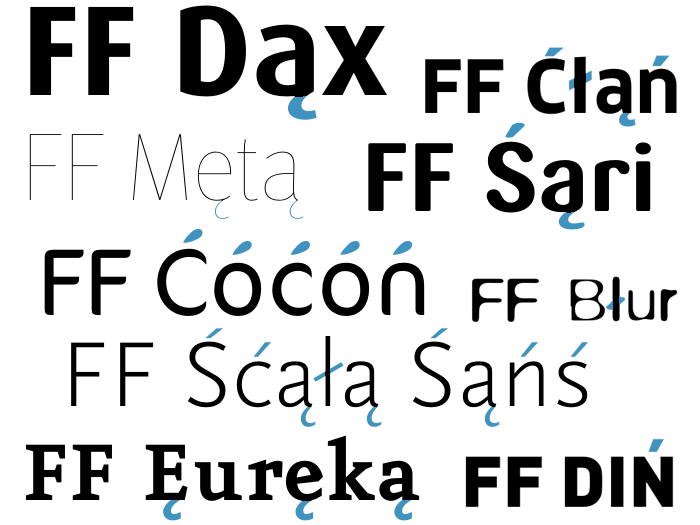
FontShop International - firma
Firmę FontShop International założyli w 1990 roku Erik Spiekermann, Joan Spiekermann oraz Neville Brody, FSI (FSI Fonts und Software GmbH) ma swoją siedzibę w Berlinie, w Niemczech. Jedną z głównych idei, która przyświecała założycielom, było stworzenie i kultywowanie biblioteki krojów pism. FSI regularnie wydaje eksperymentalną publikację typograficzną FUSE, która otrzymała różne nagrody, a także katalog fontów FontBook. FSI udziela licencji na dystrybucję fontów FontShop w wielu krajach świata. Pierwszy oddział FontShop został otwarty w 1989 roku przez Joan and Erika Spiekermann'a w Niemczech.
FontCards - pocztówki
Przez wiele lat do każdego zamówienia dołączano zestaw kolorowych pocztówek. Zostały one zaprojektowane przez twórców krojów pism dystrybuowanych przez FontShop i w ciekawy sposób ukazywały możliwości zastosowań w wybranych projektach typograficznych. Z biegiem czasu pocztówki te stały się przedmiotem kolekcjonerskim i zrodziło się zapotrzebowanie na ich dodatkowy dodruk. Do dzisiejszego dnia przygotowano ponad 100 różnych projektów pocztówek. Pewnien ich zbiór jest wciąż dostępny w postaci składanki harmonijkowej lub jako oddzielne pocztówki. Skontaktuj się z FSI lub z lokalnym przedstawicielem aby otrzymać choć jedną z nich na pamiątkę!
FontFonts - fonty
Pierwsze fonty "FontFont" pod szyldem FSI sostały wydane w roku 1990 jako fonty "5 Holenderskich Projektantów" ("5 Dutch Designers"; Erik van Blokland, Max Kisman, Martin Majoor, Just van Rossum, and Peter Verheul). Cieszą się one wciąż niesłabnącą popularnością oraz wyznaczyły jednocześnie standard jakości fontów FontFont. Reprezentują one początek biblioteki prawie 1.600 fontów, która jest obecnie znana i rozpoznawana w świecie dzięki swojej innowacyjności i najwyżej jakość współczesnych projektów typograficznych. Jedną z unikalnych cech biblioteki fontów FontFont jest szeroka różnorodność oryginalnych i niepowtarzalnych wzorów. Zakres występujących styli sięga wysokiej jakości krojów tekstowych - smakowitego kąska dla wyrafinowanej typografii, poprzez śmieszne i zabawne fonty naznaczone cechami czasów w których powstawały aż do szokujących fontów tytułowych.
Obecnie liczba fontów w ofercie sięga 1.900 odmian i wciąż się powiększa. Fonty FontFont wciąż przełamują nowe bariery jakościowe, a fima FontShop International wprowadza do swej kolekcji nowe innowacyjne projekty średnio co kwartał. To sprawia, że biblioteka fontów FontFont jest największym na świecie zbiorem oryginalnych współczesnych projektów typograficznych.